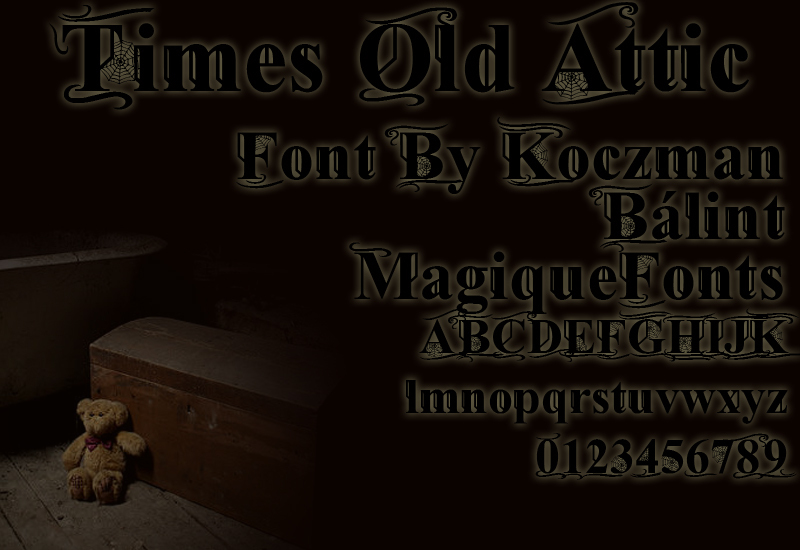
Times Old Attic Bold ist eine kostenlose viktorianische Display-Schrift, die den Flair alter Kuriositäten-Plakate einfängt. Ihre schweren Serif-Buchstaben wirken wie aus alten Zeitungen entsprungen, doch der geschwungene T-Ansatz und die spinnwebartigen Details verleihen ihr einen gotischen Showcard-Charakter – das Ergebnis ist ein theatralischer, leicht gespenstischer Look.
Sie eignet sich perfekt für Poster-Überschriften, Halloween-Branding, Buchcover, Pub-Schilder und Veranstaltungs-Flyer, bei denen es mehr auf den historischen Ton als auf Neutralität ankommt. Da es sich um eine kostenlose Schrift handelt, funktioniert sie zudem hervorragend für Titelkarten, Kapitelanfänge und kurze, logoartige Schriftzüge, da die ornamentalen Details schnell eine starke Wirkung erzielen, ohne dass viel Text nötig ist.
Präsentation und Schriftprobe von Times Old Attic Bold